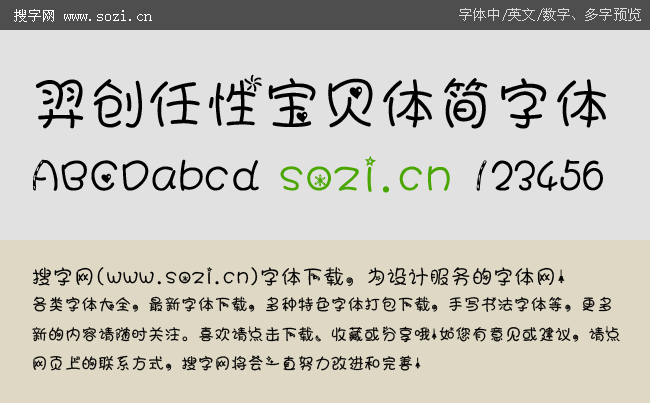
羿創(chuàng)任性寶貝體簡字體
搜字網(wǎng)給大家提供一款羿創(chuàng)任性寶貝體簡字體手機(jī)中文字體下載。這款手機(jī)字體是以一款POP風(fēng)格的卡通字體為原形,字體間嵌入了可愛的卡通圖案,是非?蓯鄣囊豢钭煮w,特別適合喜歡手機(jī)字體個性一些的朋友在手機(jī)上安裝使用。